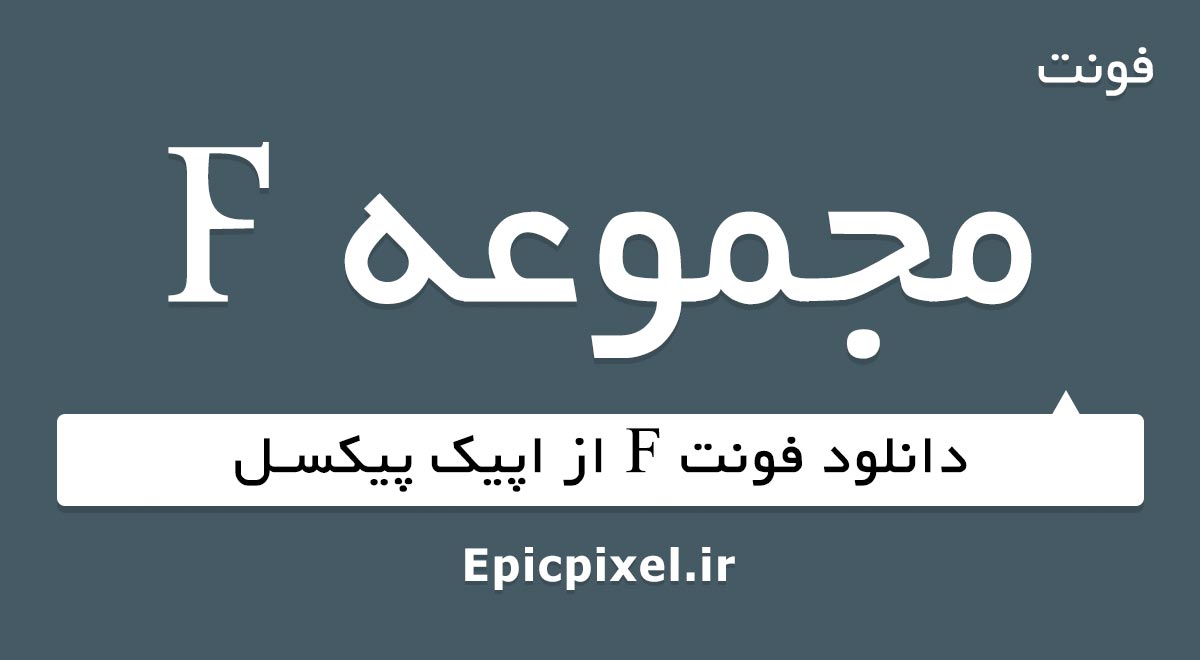
مجموعه کامل فونت های سری F (+408 فونت)
مجموعه کامل فونت های سری F (فونت های مریم) شامل بیش از ۴۰۸ فونت فارسی رایگان است که به طور خاص برای محیط هایی طراحی شده اند که از تایپ مستقیم فارسی پشتیبانی نمی کنند، مانند نرم افزار اتوکد. این فونت ها، که اغلب با ابزارهای فارسی نویس (مانند کدفا) استفاده می شوند، امکان تایپ و پرینت بدون مشکل متن فارسی را در این برنامه ها فراهم می کنند. این مجموعه برای سیستم عامل ویندوز بهینه شده است.
فونت های سری F که عموماً به نام “فونت های مریم” شناخته می شوند، یک راه حل قدیمی اما کاربردی برای مشکل فارسی نویسی در نرم افزارهایی هستند که به صورت بومی از زبان فارسی پشتیبانی نمی کنند. این مجموعه بزرگ شامل بیش از ۴۰۸ فونت متنوع است که امکانات گسترده ای را برای کاربران فراهم می کند.
کاربرد اصلی و نحوه عملکرد:
- نیاز به فارسی نویس: برخلاف فونت های مدرن OpenType که مستقیماً در برنامه هایی مانند Microsoft Word، Adobe Photoshop و… پشتیبانی می شوند، فونت های سری F برای فعال سازی قابلیت فارسی نویسی در محیط هایی مانند اتوکد، نیاز به یک برنامه فارسی نویس واسط دارند.
مزایای استفاده از فونت های سری F:
- راه حل برای نرم افزارهای قدیمی: این فونت ها راه حلی حیاتی برای فارسی نویسی در نرم افزارهای قدیمی یا تخصصی (مانند نسخه های خاص اتوکد) هستند که از یونیکد فارسی به درستی پشتیبانی نمی کنند.
- تنوع بالا: با بیش از ۴۰۰ فونت، این مجموعه تنوع بسیار زیادی از سبک های نوشتاری (فانتزی، رسمی، خطی و…) را ارائه می دهد که دست طراح را در انتخاب فونت مناسب باز می گذارد.
- پشتیبانی از کدفا: فونت های مریم به طور کامل با فارسی نویس کدفا (مخصوص اتوکد) سازگار هستند و امکان تایپ فارسی با بیش از ۹۰۰ فونت را در اتوکد فراهم می کنند.
کاربردهای مجموعه فونت های سری F
مجموعه فونت های سری F (فونت های مریم) به طور خاص برای رفع نیازهای تایپ فارسی در سناریوهای زیر مفید هستند:
- نرم افزارهای طراحی مهندسی (مانند اتوکد): اصلی ترین و شناخته شده ترین کاربرد این فونت ها، امکان فارسی نویسی در نرم افزار اتوکد با کمک فارسی نویس هایی مانند کدفا است. این امر مشکل نمایش و پرینت متن فارسی در نقشه ها و طرح های مهندسی را حل می کند.
- برنامه های گرافیکی قدیمی: در نسخه های قدیمی تر نرم افزارهای گرافیکی که پشتیبانی ضعیفی از فارسی داشتند، این فونت ها می توانستند به عنوان یک راه حل واسط برای وارد کردن متن فارسی به کار روند.
- سیستم های عامل خاص: در برخی محیط ها یا سیستم عامل های خاص که پشتیبانی از زبان فارسی بومی نیست، این فونت ها می توانند با کمک ابزارهای فارسی نویس، امکان تایپ فارسی را فراهم کنند.
- نیازهای خاص پرینت: تضمین پرینت بدون مشکل متن فارسی در محیط هایی که فونت های استاندارد ممکن است در هنگام چاپ دچار مشکل شوند.